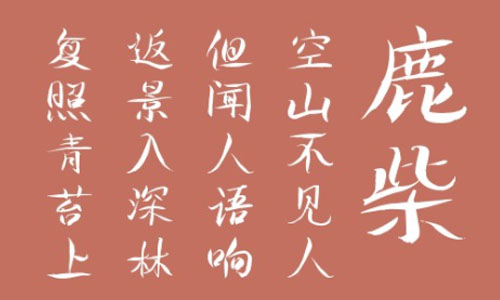
南構(gòu)鮑貴芬柳韻字體是一款由鮑貴芬老師書寫書法寫意字體,貴芬寫意畫,寥寥數(shù)筆墨韻鳴在筆頭,那樣輕巧的攝魂奪魄,一筆筆對準自然界的一草一木一石一物,不經(jīng)意卻小心地將形神作一體整合。
觀鮑貴芬畫作,尤如觀賞美麗的風(fēng)景,有一種心曠神怡的享受。其畫清新淡雅,構(gòu)圖飽滿,技法老練又不失女性柔美。鮑貴芬作畫很慢,但筆觸表達力卻很強,有時只見她三三兩兩的勾勒、星星點點的渲染,構(gòu)思奇妙、立意深遠的畫面就躍然于紙上。